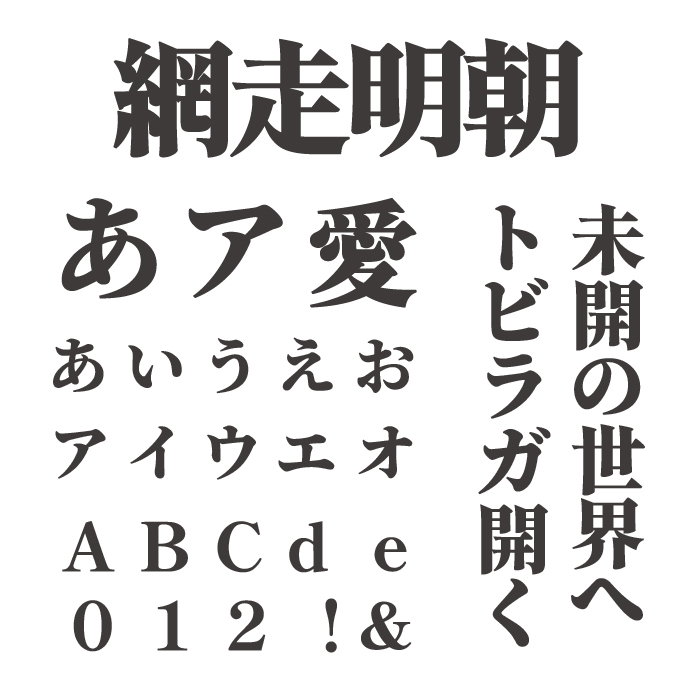
網走明朝
網走明朝フォントは、明朝体の優美さに、力強い筆のタッチを大胆に加えた個性的な極太明朝体フォントです。
Noto Serif(源ノ明朝)をベースにして加筆され、超極太な明朝体に仕上げられているフォントです。他にはないような極太な明朝となっています。フリーフォントで極太明朝体フォントってなかなかないので、重宝するフォントです。
上品さと力強さ、そして少しの「和」の情緒を同時に表現したいシーンにぴったりです。 例えば、高級旅館のパンフレット、伝統工芸品の紹介、あるいは文学作品のタイトルなど、風格と洗練された美しさが求められるデザインにぴったりです。
収録文字は、漢字・ひらがな・カタカナ・アルファベット・数字・記号が収録。